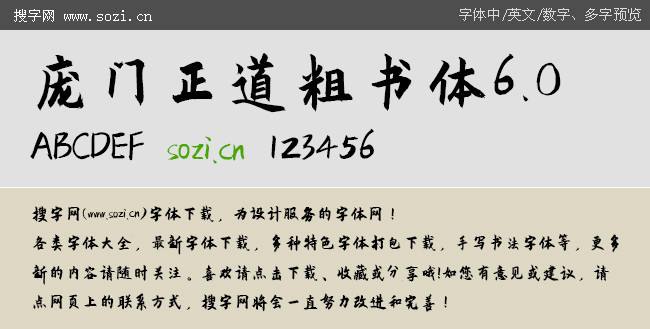
龐門正道粗書(shū)體6.0
搜字網(wǎng)給大家提供一款龐門正道粗書(shū)體中文字體下載,龐門正道粗書(shū)體是一款不錯(cuò)的手寫(xiě)藝術(shù)字體,本款為升級(jí)版本,這款字體筆觸較為粗實(shí),書(shū)寫(xiě)端正大氣,重要的是可以免費(fèi)商用,適合應(yīng)用于藝術(shù)設(shè)計(jì)、平面宣傳設(shè)計(jì)、網(wǎng)頁(yè)設(shè)計(jì)、海報(bào)設(shè)計(jì)等應(yīng)用。